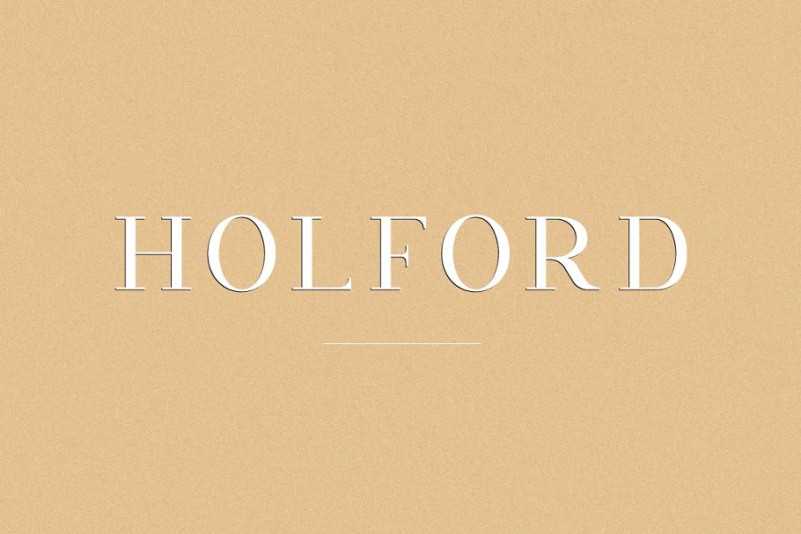
Holford Serif Font – Fonte Grátis
Holford Serif Font
Esta é uma coleção de serif fonts criada pela Surplus Type Co., com movimento natural que resulta em uma aparência elegante e sofisticada para seus projetos. Este tipo de fonte limpa destaca-se por seu tracinho fino e caracteres multilíngues, perfeito para criar designs de alto padrão como logotipos e marcas, embalagens e, claro, muitas outras aplicações. Sujeitando-se à natureza da descrição original em inglês, esta font é ideal para quem busca uma aparência sofisticada em seu próximo projeto gráfico.